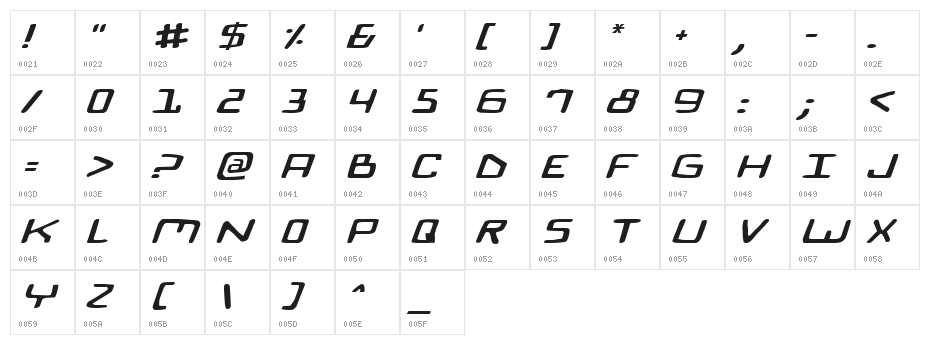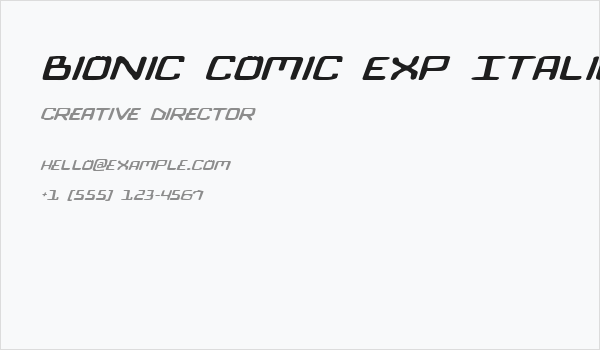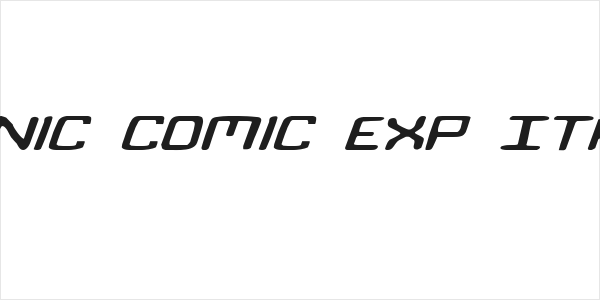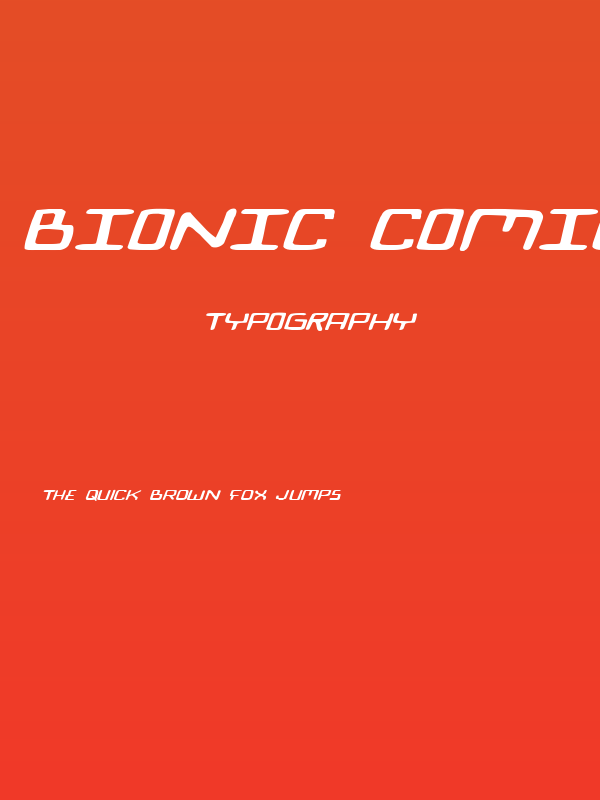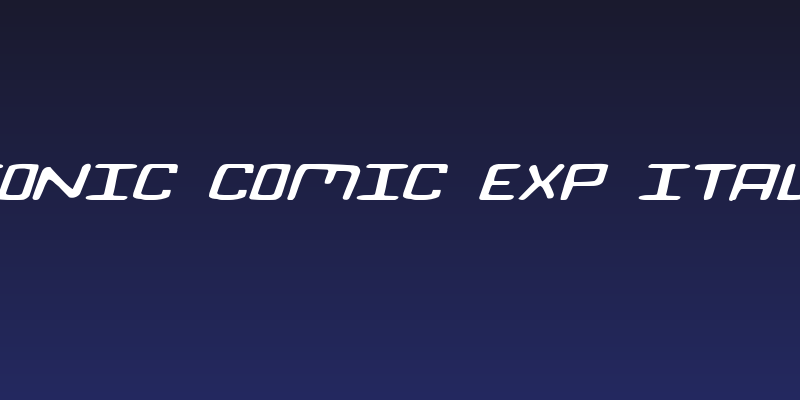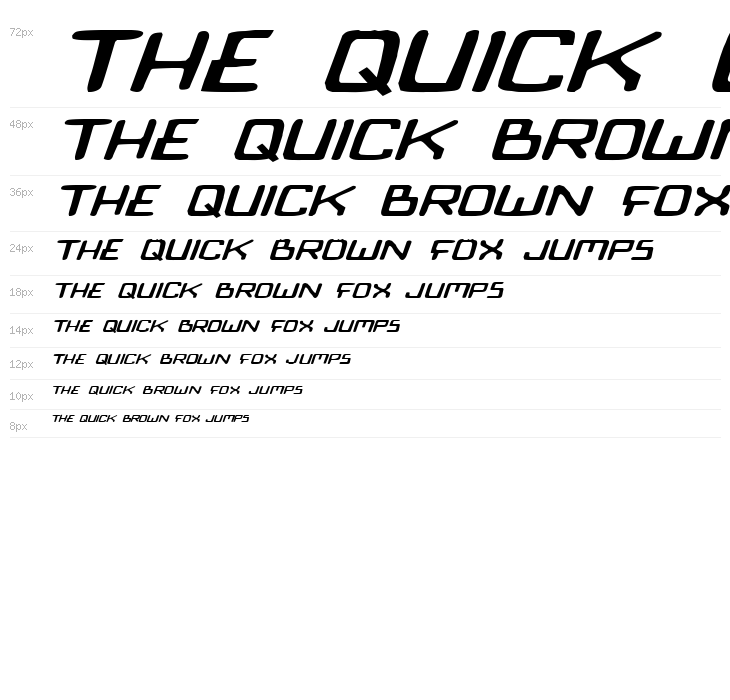
Bionic Comic Exp Italic Font
✎ Capitals
| Nume | Bionic Comic Exp Italic |
| Greutate | Exp Italic |
| Categorii | Capitals |
| Lățime | Expanded |
| Proiecte propuse | Ideal for tech branding, comic-style graphics, and dynamic posters. |